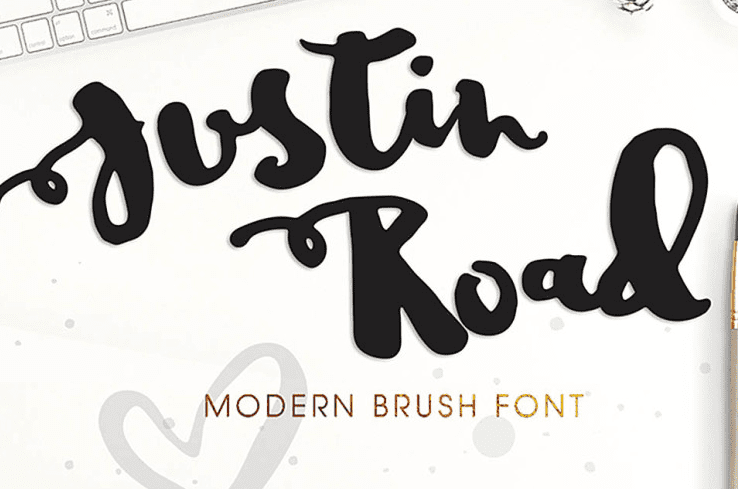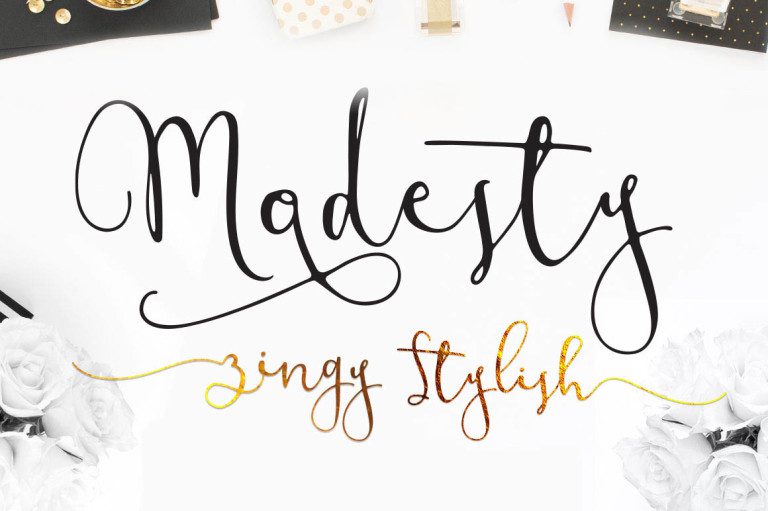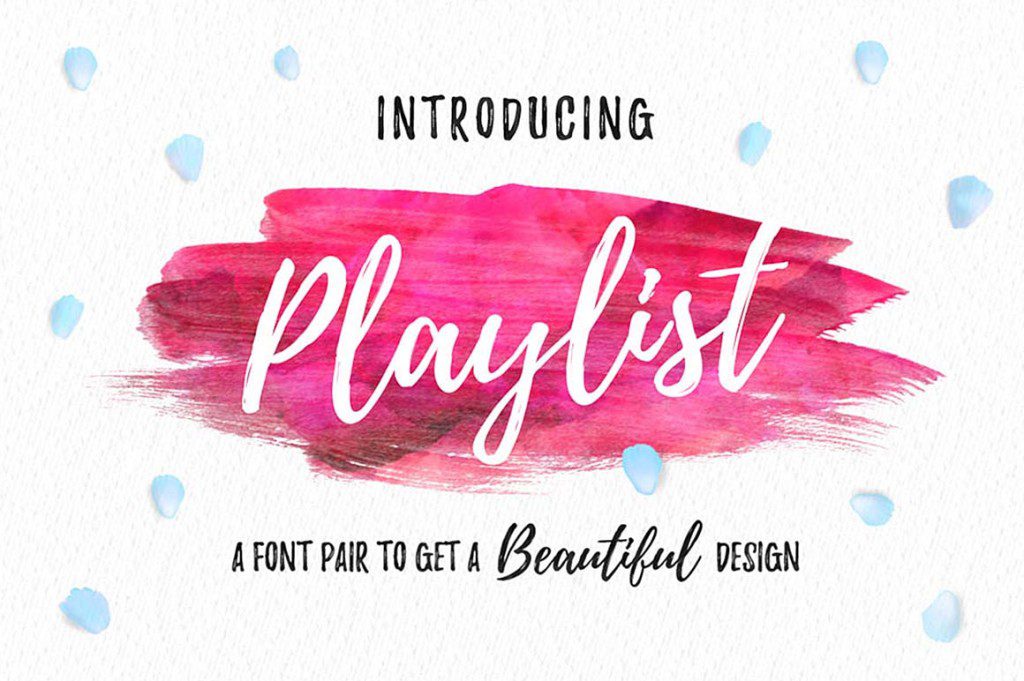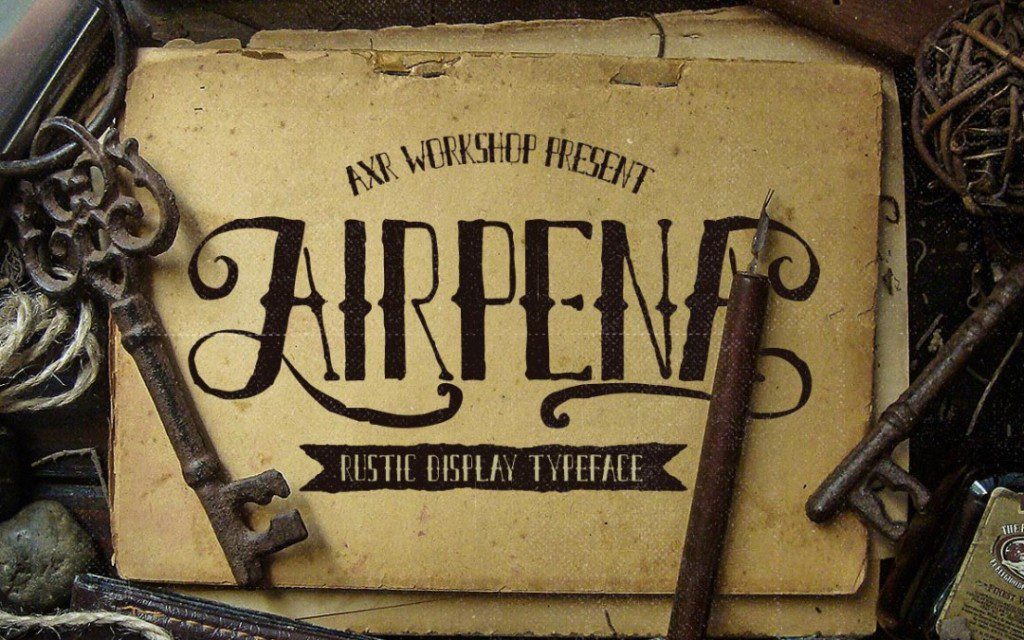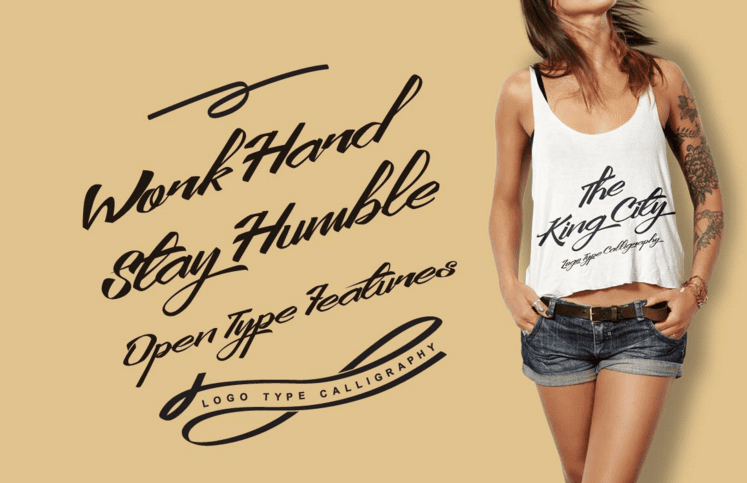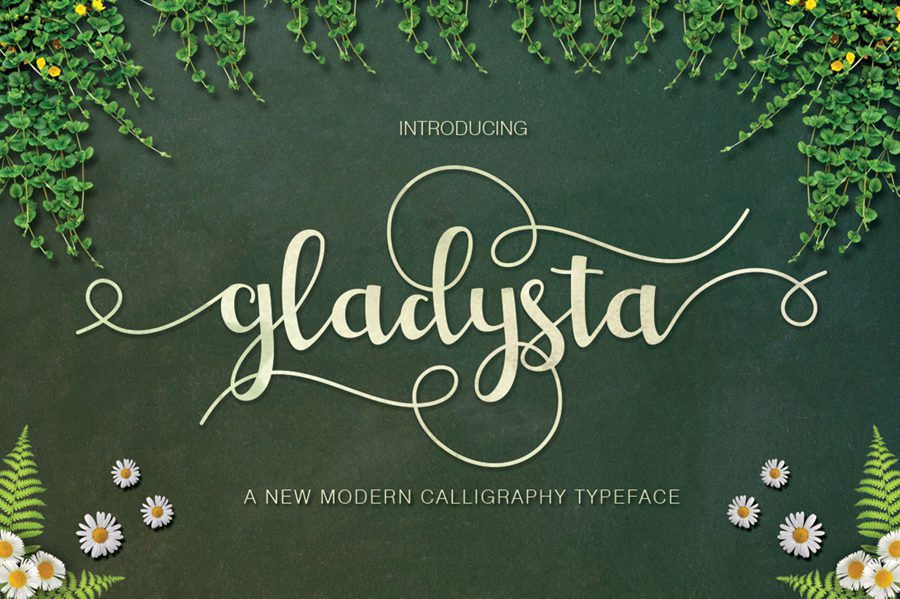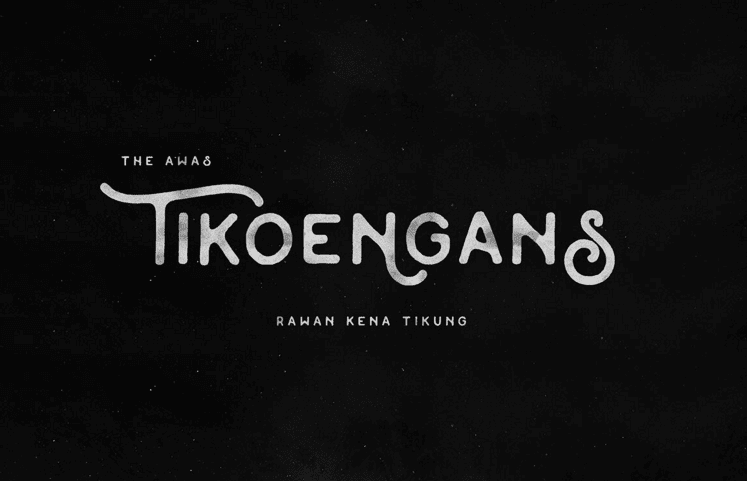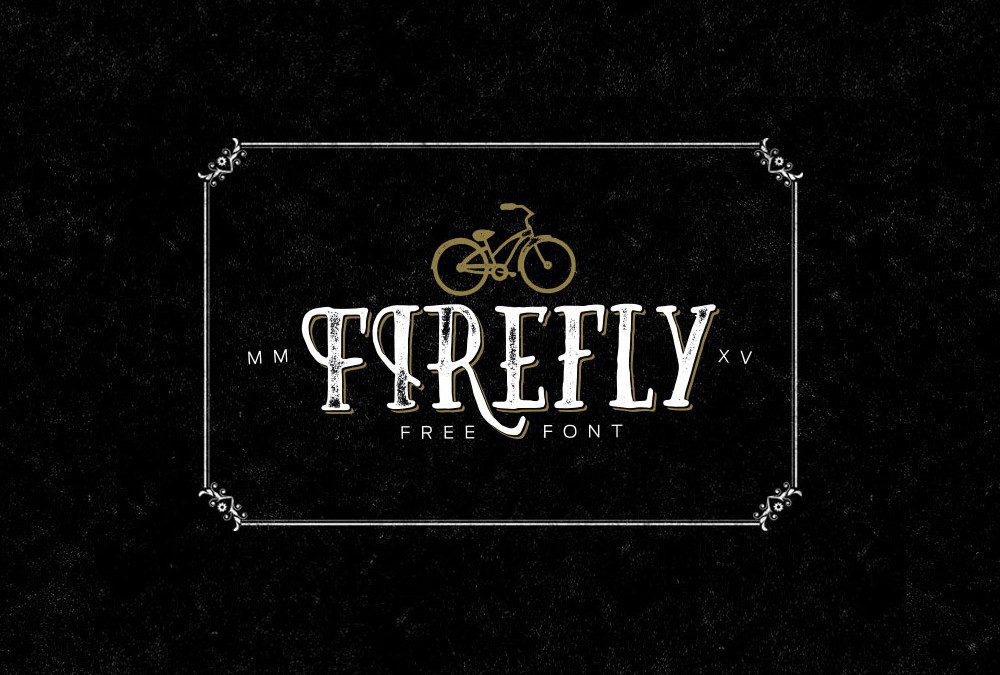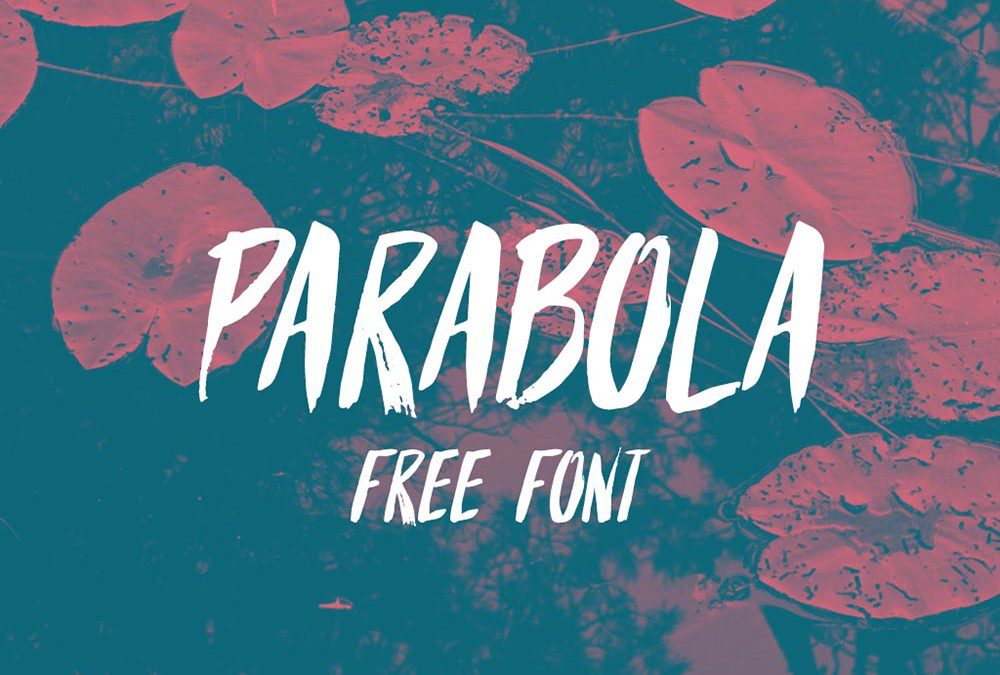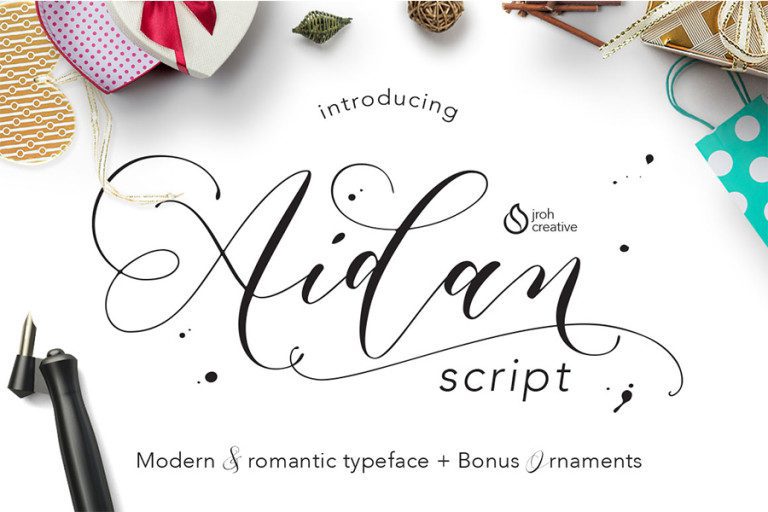
20+ แบบอักษรฟรีที่ดีที่สุดสำหรับนักออกแบบที่คุณจะพบว่ามีประโยชน์
เผยแพร่แล้ว: 2016-03-16เพื่อน! วันนี้เรากลับมาพร้อมกับคอลเลกชัน แบบอักษรฟรีที่ดีที่สุด 20 แบบสำหรับนักออกแบบ ที่คุณจะพบว่ามีประโยชน์ แบบอักษรเหล่านี้เป็นแบบอักษรที่สวยงาม ทันสมัย และมีเอกลักษณ์เฉพาะตัว และสามารถดาวน์โหลดและใช้งานได้ฟรี ลองดูและเพิ่มลงในคอลเล็กชันแบบอักษรของคุณตอนนี้ แน่นอนว่าคุณจะพบว่าสิ่งเหล่านี้มีประโยชน์ในอนาคต
1. แบบอักษรที่เขียนด้วยลายมือฟรี – Airpena
นี่คือแบบอักษรฟรีที่ได้รับแรงบันดาลใจจากตัวอักษรที่วาดด้วยมือที่มีสนิมและมีรอยตำหนิที่ใช้กับมอเตอร์ไซค์ย้อนยุค มันมาพร้อมกับตัวอักษรเต็มสลับกันสำหรับตัวพิมพ์ใหญ่ (ด้านหน้า & end) และตัวพิมพ์เล็ก (end)
2. Luxia – ฟอนต์ฟรีสมัยใหม่
ดู Luxia ซึ่งเป็นเกมซานเซอริฟสมัยใหม่ที่มีตัวละครฟุ่มเฟือย ประกอบด้วย 3 รูปแบบ: กึ่งหนา กึ่งเฉียง อย่าลังเล! ดาวน์โหลดแบบอักษรฟรีและสร้างหัวเรื่องที่สวยงามโดยใช้แบบอักษร
3. อพยพ – แบบอักษรฟรี
Exodus – แบบอักษรฟรี พร้อมเส้นสายที่หรูหรา มันจะช่วยให้คุณสร้างชุดอักขระที่เป็นเอกลักษณ์เฉพาะตัวสำหรับโลโก้และหัวเรื่อง ในขณะที่ให้การควบคุมอย่างเต็มที่กับผู้ออกแบบ freebie ออกแบบโดย Andrew Herndon
4. โซเฟีย – แบบอักษรสคริปต์พู่กัน Handlettered
Sophia – ดาวน์โหลดแบบอักษร Handlettered Brush Script ใหม่ฟรี โดย Emily Spadoni ผู้มากความสามารถ ในใจของฉัน แบบอักษรนี้หวานมาก ทะลึ่ง และโทรมเล็กน้อย โซเฟียช่วยให้คุณสร้างสไตล์คำที่ตกแต่งเองได้อย่างง่ายดาย ดาวน์โหลดฟรีภายในไม่กี่คลิกและใช้กับโปรแกรมต่างๆ มากมาย เช่น Photoshop, InDesign, Illustrator และ Microsoft Word และอีกมากมาย
5. แบบอักษร Brusher ฟรี
นี่คือ ฟอนต์ดาวน์โหลดฟรีพร้อม แปรงที่ทันสมัยและโดดเด่น ซึ่งจะลงตัวกับโปรเจกต์การออกแบบในอนาคตของคุณ ทรัพยากรประกอบด้วยร่ายมนตร์ 100 อันที่สร้างขึ้นด้วยจังหวะที่แม่นยำและเส้นที่เรียบซึ่งจะทำให้ข้อความของคุณดูเป็นธรรมชาติ
6. Wask New – Condensed, Sans Serif ฟรีฟอนต์
freebie ออกแบบโดย Vasilis Skandalos แบบอักษรฟรีประกอบด้วยน้ำหนักสองตัวและแม้แต่สไตล์ตัวเอียง เหมาะสำหรับวัตถุประสงค์ทางธุรกิจ การโฆษณา บรรจุภัณฑ์ และสำหรับสิ่งพิมพ์
7. แบบอักษร Parabola ที่เขียนด้วยลายมือฟรี
Parabola เป็น ฟอนต์ฟรีที่เขียนด้วยลายมือ ที่ยอดเยี่ยมสำหรับโปสเตอร์และพาดหัวข่าว แบบอักษรนี้เป็นสไตล์แปรงที่ดีมากซึ่งมีให้ในรูปแบบ: OTF TTF และชุดแบบอักษรบนเว็บ ดูดีสำหรับโครงการทุกประเภท โดยเฉพาะอย่างยิ่งโครงการออกแบบที่ต้องการแบบอักษรที่เขียนด้วยลายมือที่มีความเป็นส่วนตัว
8. หิ่งห้อย: แบบอักษรวาดด้วยมือฟรี
หิ่งห้อย: ดาวน์โหลดแบบอักษรวาดด้วยมือฟรี เป็น serif ที่เล่นโวหารพร้อมด้วยบุคลิกและเสน่ห์มากมายและมาพร้อมกับร่ายมนตร์ครบชุดและทางเลือกอื่น ๆ ฟอนต์ฟรีใช้งานได้ดีกับคำพูด โลโก้ โปสเตอร์ พาดหัว เสื้อยืด และอื่นๆ อีกมากมาย!
9. แบบอักษรฟรี – Soria
มันถูกสร้างขึ้นภายใต้อิทธิพลสมัยใหม่ ใช้แบบอักษรนี้เพื่อทำให้โครงการออกแบบเว็บหรือโครงการออกแบบกราฟิกของคุณดูหรูหรา
10. แบบอักษรฟรี – Elrotex
แบบอักษรพู่กันที่เท่และไม่ซ้ำใครนี้จะทำให้การออกแบบของคุณมีลุคในแบบฉบับงานฝีมือที่น่าทึ่ง สอดคล้องกับโครงการสร้างสรรค์ใดๆ เช่น คำพูด โลโก้ บรรจุภัณฑ์ เสื้อยืด
11. แบบอักษรฟรี – Humble Rought
นี่คือแบบอักษรวินเทจสมัยใหม่ที่มีการไหลที่ไม่สมบูรณ์ซึ่งจะทำให้ข้อความของคุณดูเป็นธรรมชาติ แบบอักษรที่น่าทึ่งนี้ยังประกอบด้วยอักขระพิเศษ สัญลักษณ์ และตัวเลือกโวหารที่เลือกสรร สามารถใช้ได้กับโลโก้ บรรจุภัณฑ์ เสื้อยืด และอื่นๆ
12. แบบอักษรวินเทจฟรี – Moabhoers
ครั้งนี้เรามีความยินดีที่จะแบ่งปันกับคุณด้วย แบบอักษรวินเทจพรีเมียมแบบพรีเมียมฟรี ที่น่าทึ่ง – Moabhoers จาก Agga Swist'blnk แบบอักษรตัวพิมพ์ใหญ่ / แบบอักษรที่มีสไตล์วินเทจที่ยอดเยี่ยม นอกจากนี้ ยังมีอักขระพิเศษ
13. สคริปต์เพลย์ลิสต์ – แบบอักษรฟรี
นี่คือการ ออกแบบแบบอักษรฟรีแบบ กำหนดเองของสคริปต์ - สคริปต์เพลย์ลิสต์ นี่คือแบบอักษรสคริปต์ที่วาดด้วยมือที่ยอดเยี่ยมพร้อมสไตล์แปรง ลองดาวน์โหลดและใช้งานสำหรับโครงการต่อไปของคุณได้ตามสบาย สนุก!
14. Judas – ฟอนต์ฟรีสมัยใหม่
แบบอักษรฟรีนี้อิงจากโลโก้วง British Heavy Metal ในตำนาน มันปรับแต่งได้และคุณสามารถใช้มันกับทุกสิ่งที่คุณต้องการ
15. แบบอักษรฟรี – Gladysta Script
เป็นแบบอักษรอักษรวิจิตรสมัยใหม่ที่มีเส้นฐานการเต้น แบบอักษรนี้ผสมผสานอักษรพู่กันกับการเขียนด้วยมือแบบดั้งเดิม กลมกลืนกับตราสินค้าส่วนบุคคล นามบัตร โปสเตอร์ใบเสนอราคา และอื่นๆ
16. Aidan – สคริปต์โรแมนติก
Aidan เป็นการออกแบบ chirography ที่ทันสมัยพร้อมการเคลื่อนไหวที่โรแมนติกและโดดเด่น ตามคำเชิญงานแต่งงาน การออกแบบตามสีน้ำ นอกจากนี้ยังเหมาะกับทุกสิ่งที่ต้องการความรู้สึกเป็นธรรมชาติ แบบอักษรนี้สามารถใช้ได้ทั้งเพื่อวัตถุประสงค์ส่วนตัวและเพื่อการค้า
17. ความสุภาพเรียบร้อย – การเขียนพู่กัน
ทำให้โปรเจ็กต์ใหม่ของคุณน่าประทับใจด้วย Free Font ใหม่ – Modesty นี่คือแบบอักษรคัดลายมือที่มีการเคลื่อนไหวที่โรแมนติกและโดดเด่น สอดคล้องกับการสร้างแบรนด์ การออกแบบบล็อก การออกแบบโฆษณาสมัยใหม่ สมุดภาพ และอื่นๆ อย่าลังเลที่จะใช้เพื่อวัตถุประสงค์ส่วนตัวและเชิงพาณิชย์
18. Something Wild – แบบอักษรฟรี
นี่คือแบบอักษรที่เขียนด้วยลายมือที่มีจิตวิญญาณแห่งป่าอย่างแท้จริงซึ่งจะทำให้การออกแบบของคุณมีเอกลักษณ์และโดดเด่นท่ามกลางฝูงชน แน่นอนว่ามันจะสร้างความประทับใจให้ผู้ชมของคุณอย่างลึกซึ้ง Something Wild มาในรูปแบบยอดนิยมทั้งหมด สิ่งที่ถูกต้องสำหรับคุณหากคุณต้องการเพิ่มความรู้สึกดิบๆ ให้กับงานออกแบบของคุณ!
20. King City – สคริปต์การประดิษฐ์ตัวอักษรที่ไม่ซ้ำใครฟรี
King City - ฟอนต์ฟรีสคริปต์การประดิษฐ์ตัวอักษรที่ไม่ซ้ำใคร ซึ่งเหมาะสำหรับการออกแบบ การออกแบบองค์ประกอบ งานแต่งงาน สติ๊กเกอร์ และงานที่ยอดเยี่ยม งานอีเวนต์ เสื้อยืด โลโก้ ป้าย ฯลฯ ... ฟอนต์เป็นฟอนต์แบบรวมทางเลือกและปรับแต่งได้ง่าย
21. Justin Road – ฟรี Brush Font Family
แบบอักษรนี้เหมาะสำหรับการสร้างแบรนด์ การออกแบบสเตชันเนอรี สมุดภาพสมัยใหม่ ผู้วางแผน ชีวิตโครงการหรือการออกแบบสมุดบันทึก การออกแบบบล็อก งานแต่งงาน กิจกรรมพิเศษ ความต้องการตัวอักษรใดๆ การออกแบบโฆษณาสมัยใหม่ บัตรเชิญ และอื่นๆ